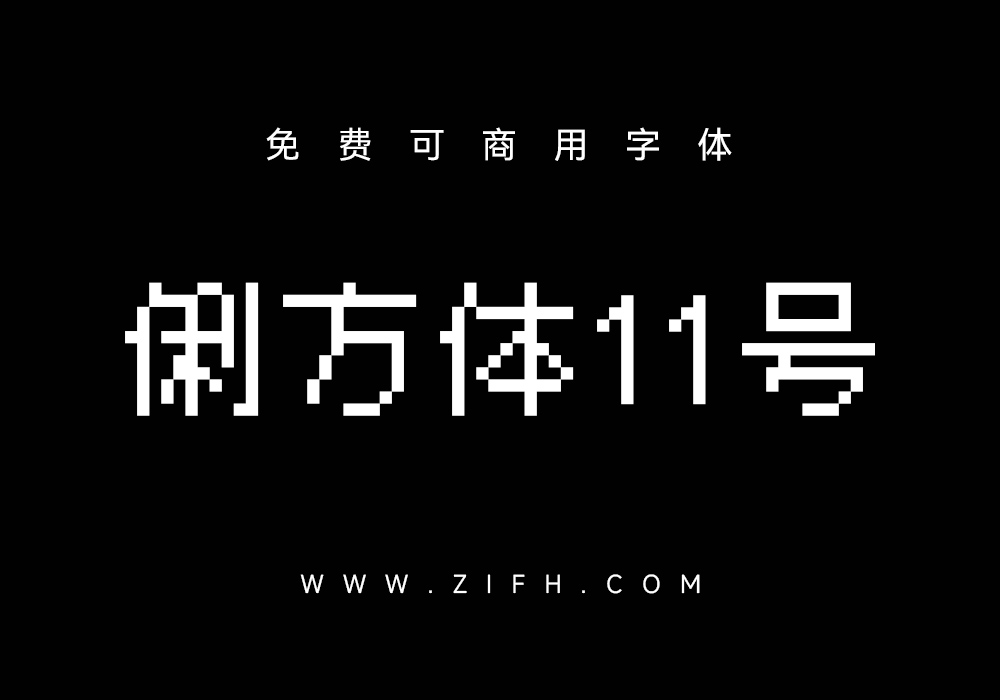
本字型基于 SIL Open Font License 1.1 改造 M⁺ BITMAP FONTS 所发布的 M⁺ gothic 12r 开源字型,授权条款公开发布。关于授权合约的详细内容,请详读授权文件档(OFL.txt)本字型以日文字型 M⁺ gothic 12r 为基础替繁体中文进行修改与扩充,其中包括适用繁体中文的标点符号以及较符合台湾习惯的字形等。